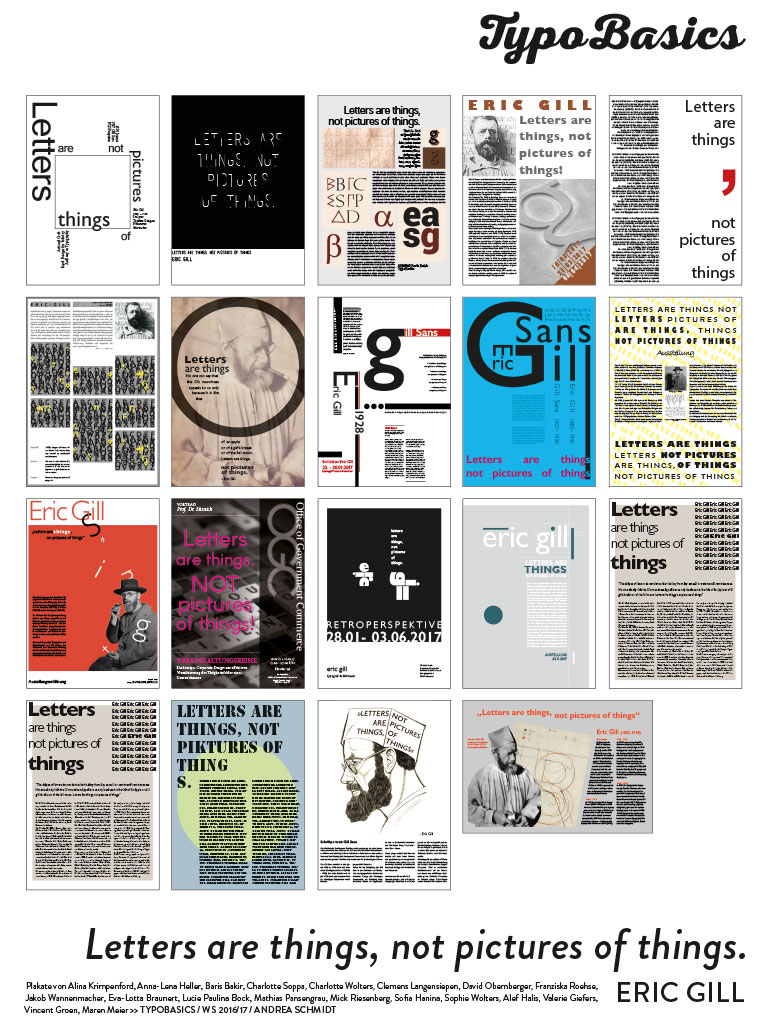
Das Typografieseminar an der Leibniz-Universität Hannover bot unter dem Thema »Letters are things, not pictures of things« (Zitat: Eric Gill) einen Überblick über das Gestalten mit Schrift. Ausgehend vom Schreiben und Zeichnen bis hin zu komplexen digitalen Layouts wurden folgende Themen behandelt: Typografische Grundlagen und Fachbegriffe, Schriftgeschichte, Klassifizierung von Schriften, Mikrotypografie und Anwendung von Schrift im digitalen Medium. Im Spannungsfeld zwischen manuellem und digitalem Arbeiten, zwischen Schreiben von Schrift mit Werkzeugen und Anwenden von Schrift in Layoutprogrammen, haben die Teilnehmenden ein eigenes Konzept für eine Buch-Publikation entwickelt.